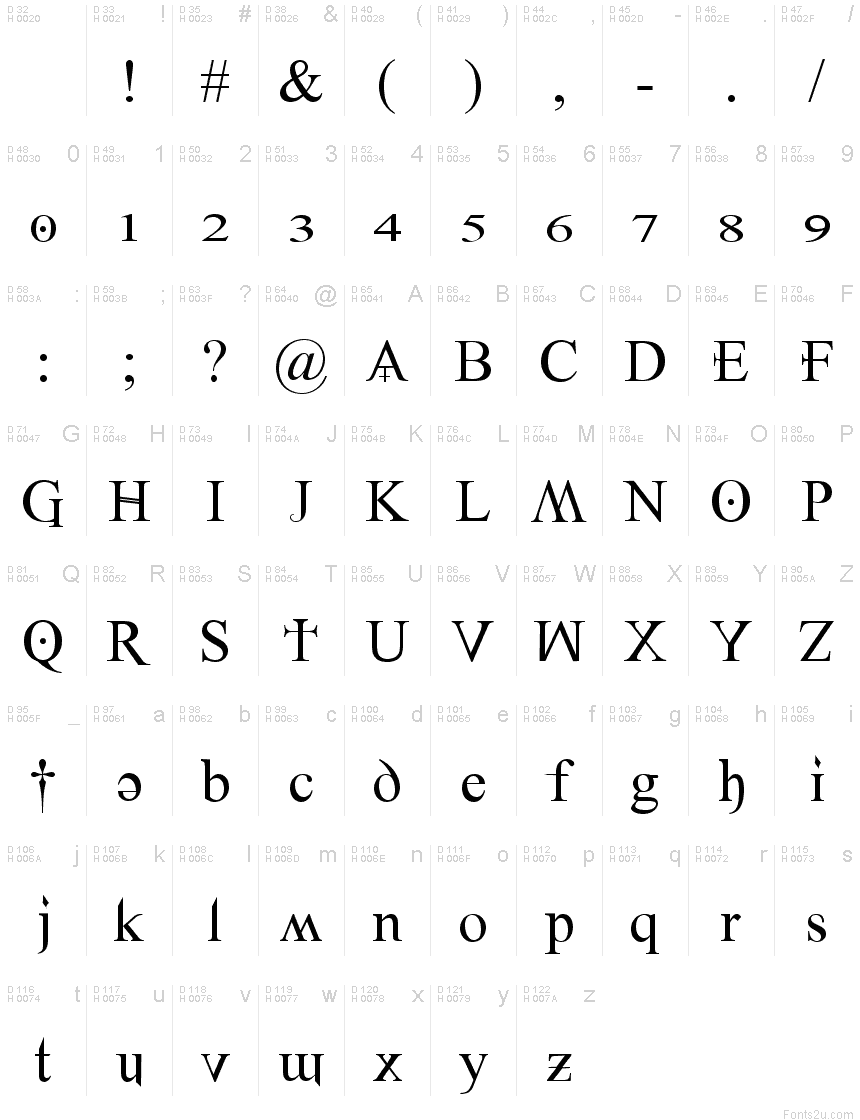
Denial2 od SDFonts to darmowy, szeryfowy krój pisma w stylu retro, który przekształca klasyczne, niemal książkowe kształty w coś znacznie dziwniejszego i bardziej teatralnego. Wysokie, wąskie litery wydają się lekko przekrzywione, a ostre, przypominające ostrza kreski zderzają się z gładkimi, zaokrąglonymi łukami, nadając tekstom nastrojowy, noir-owy charakter. W tych kształtach drzemie napięcie – eleganckie, a jednocześnie niepokojące – które sprawia, że nawet pojedyncze słowo wygląda jak plansza tytułowa z zapomnianego filmu art-house’owego.
Używając Denial2, Twój tekst nie tylko spoczywa na stronie; on się po niej przechadza. Ten darmowy font świetnie sprawdzi się na plakatach horrorów, okładkach thrillerów, eksperymentalnych okładkach albumów, mrocznych logotypach, nagłówkach magazynów i czołówkach filmowych. W mniejszych rozmiarach łącz Denial2 z prostym, mało kontrastowym krojem bezszeryfowym, aby zachować czytelność, pozwalając jednocześnie tym dziwnym, wyrazistym wersalikom i krzywiznom budować dramaturgię.